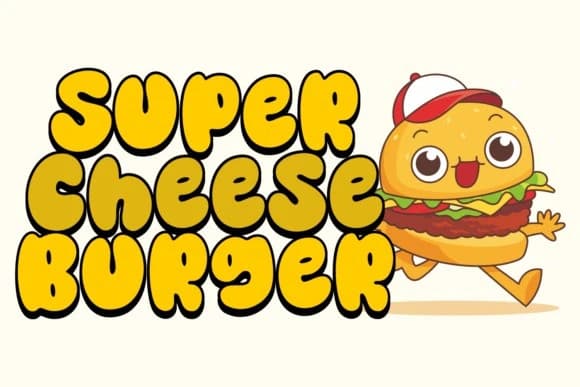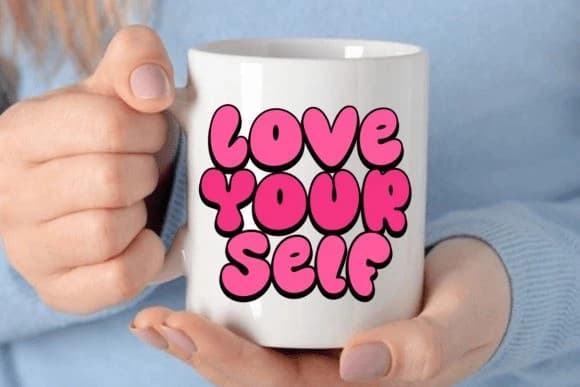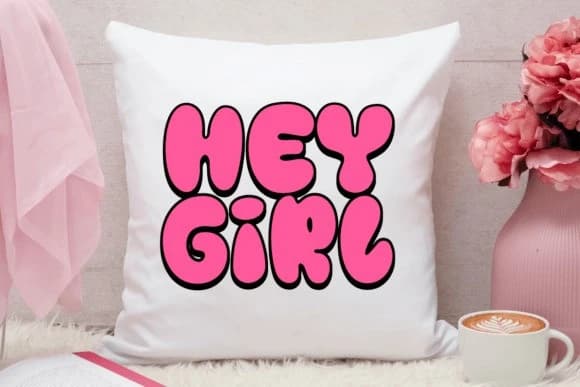
Silky Cheese Eğlenceli Yazı Tipi
Silky Cheese Playful Font, sevimli ve tuhaf bir gösterim yazı tipidir. Tasarımlarınıza inanılmaz neşeli bir dokunuş katacak. Bu güzel gösterim yazı tipini her bir yaratıcı fikrinizin üzerine ekleyin ve bunun onları öne çıkardığını görün!
Silky Cheese Playful Font, tatlı ve tuhaf bir gösterim yazı tipidir. Tasarımlarınıza son derece neşeli bir dokunuş katacaktır. Bu güzel gösterim yazı tipini her bir yaratıcı fikrinizde kullanın ve bunun onları öne çıkardığını görün!